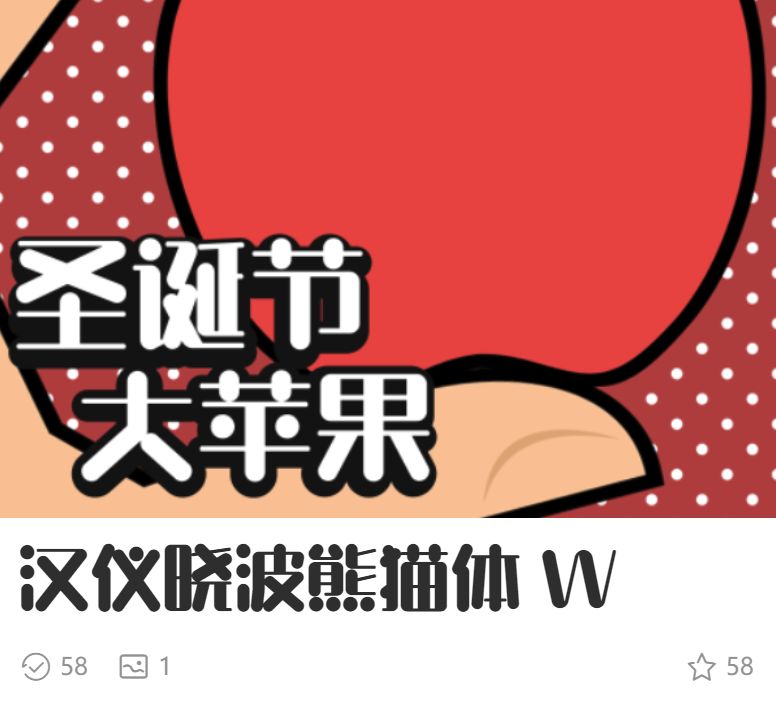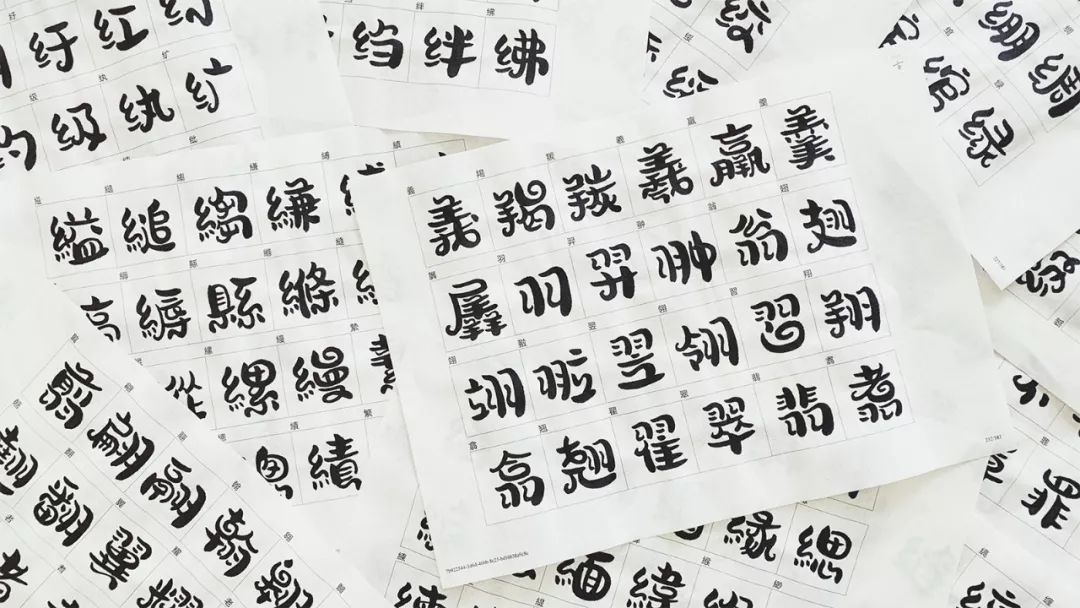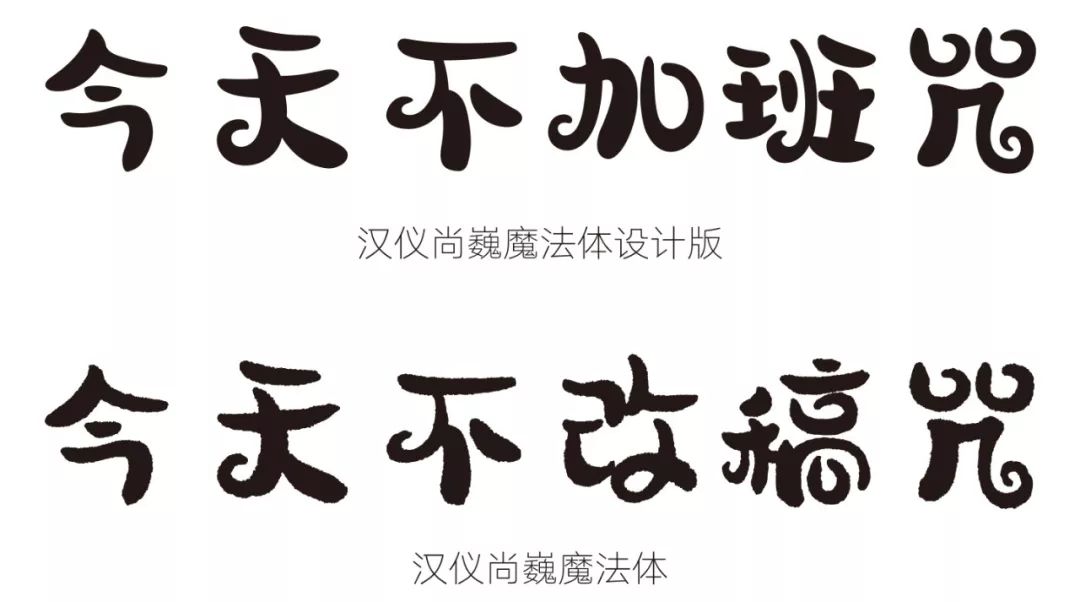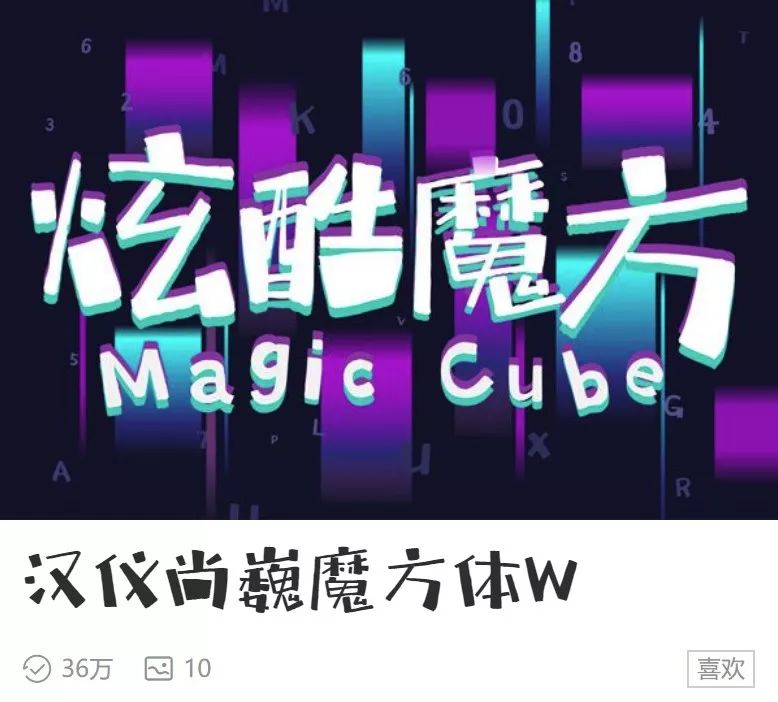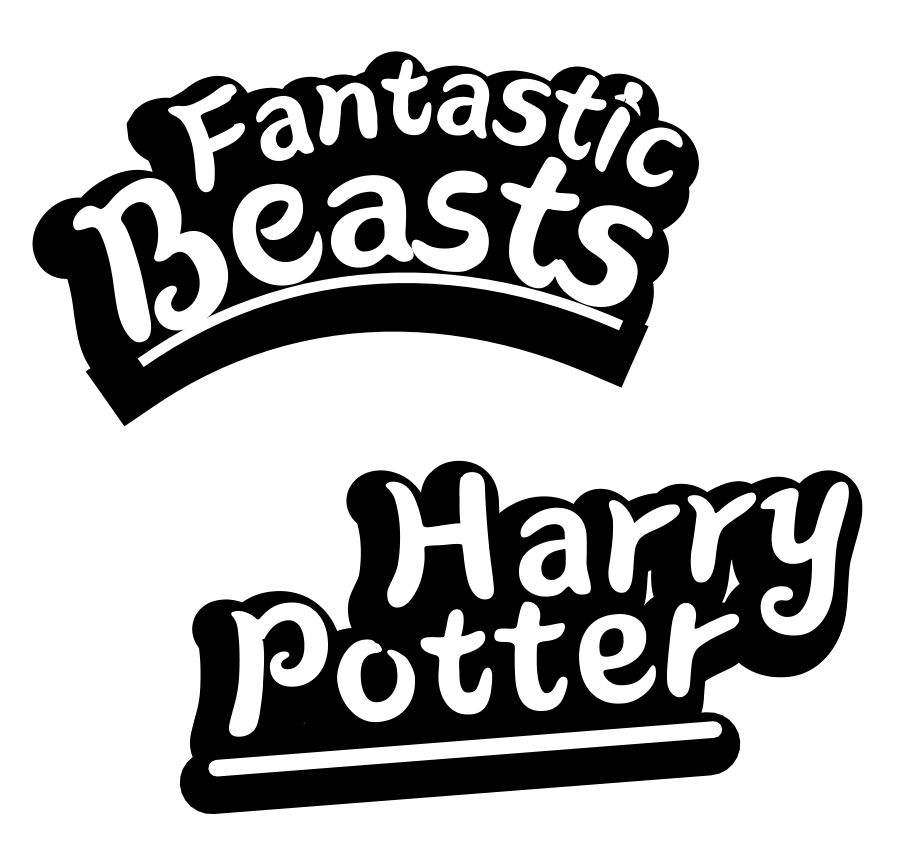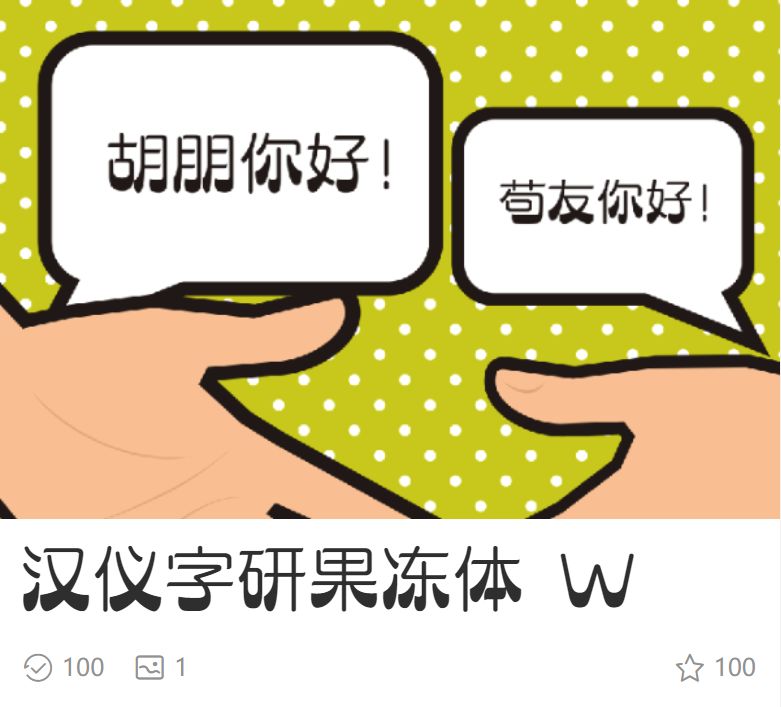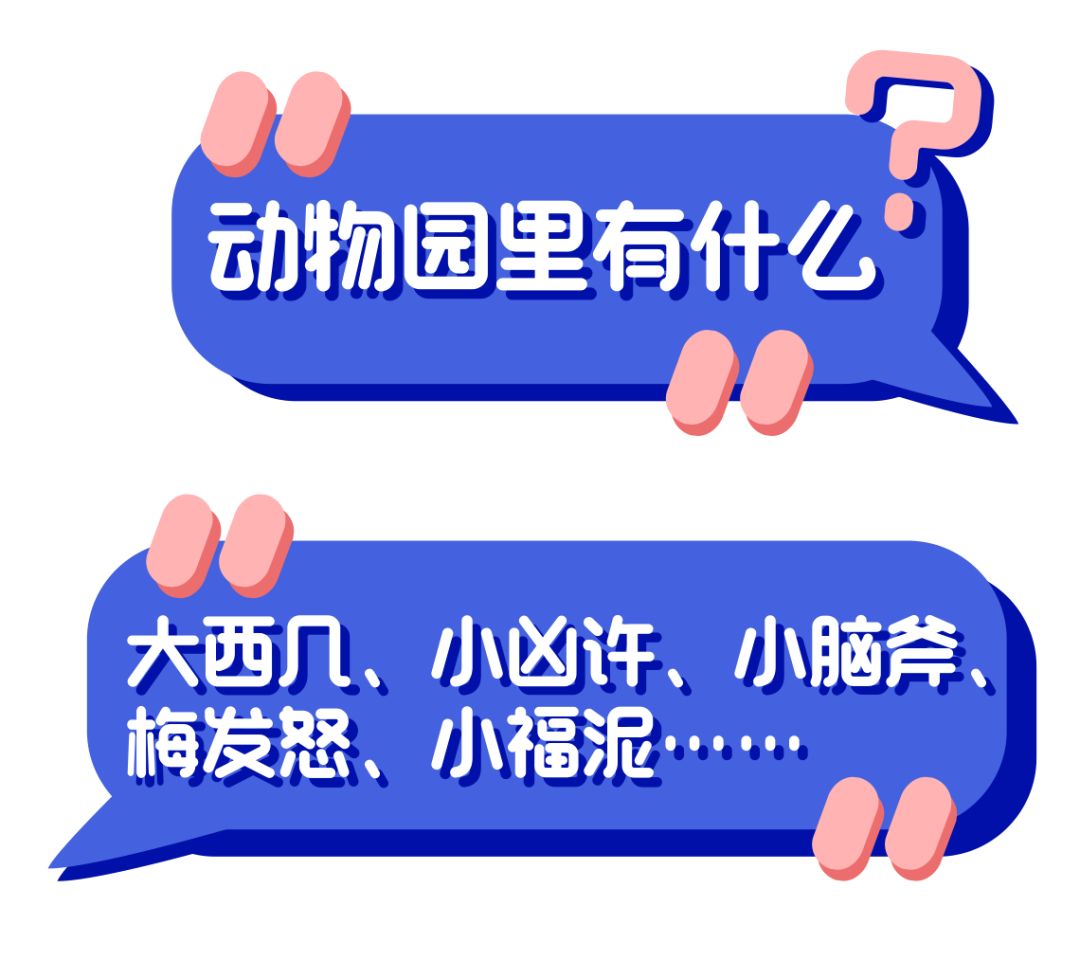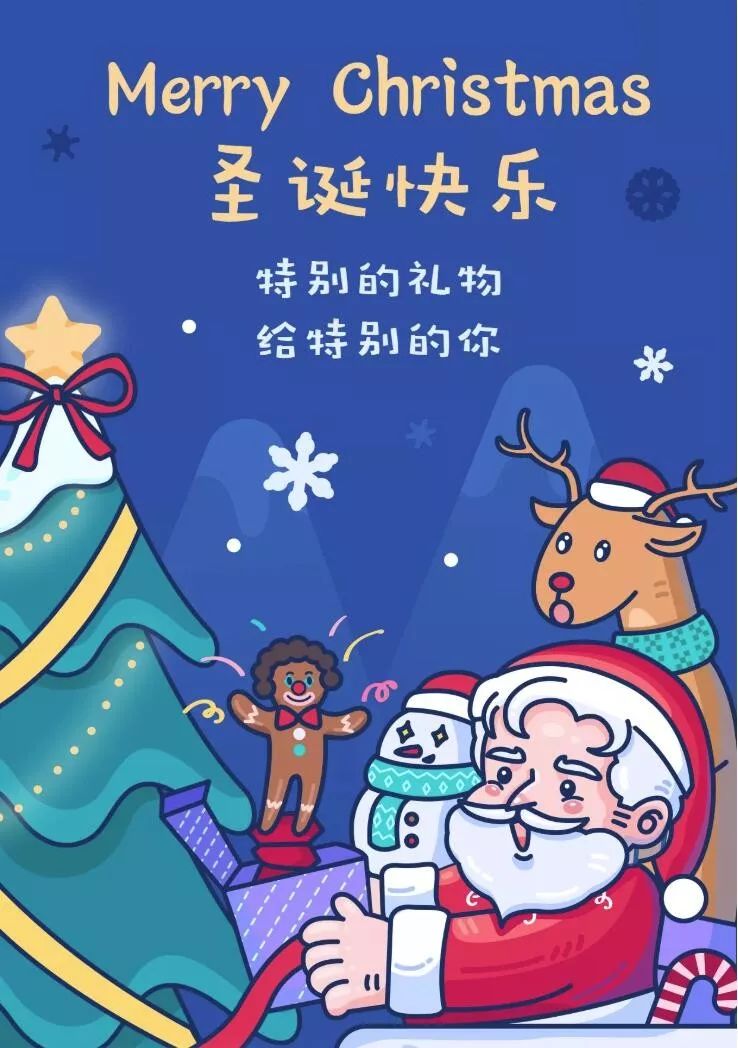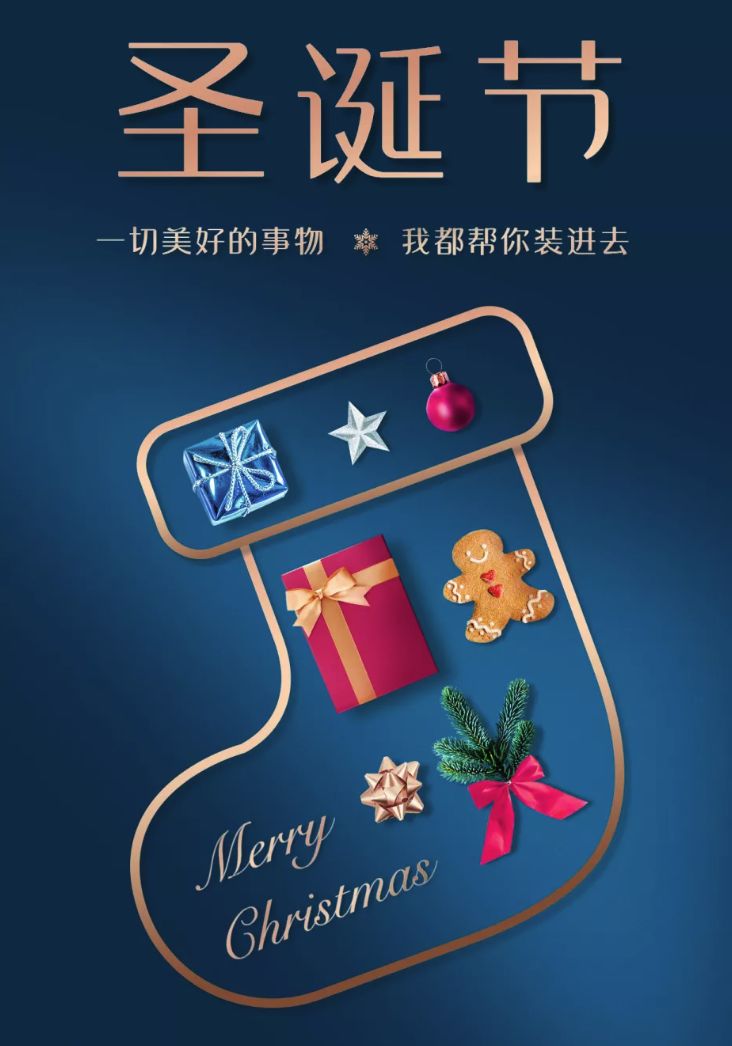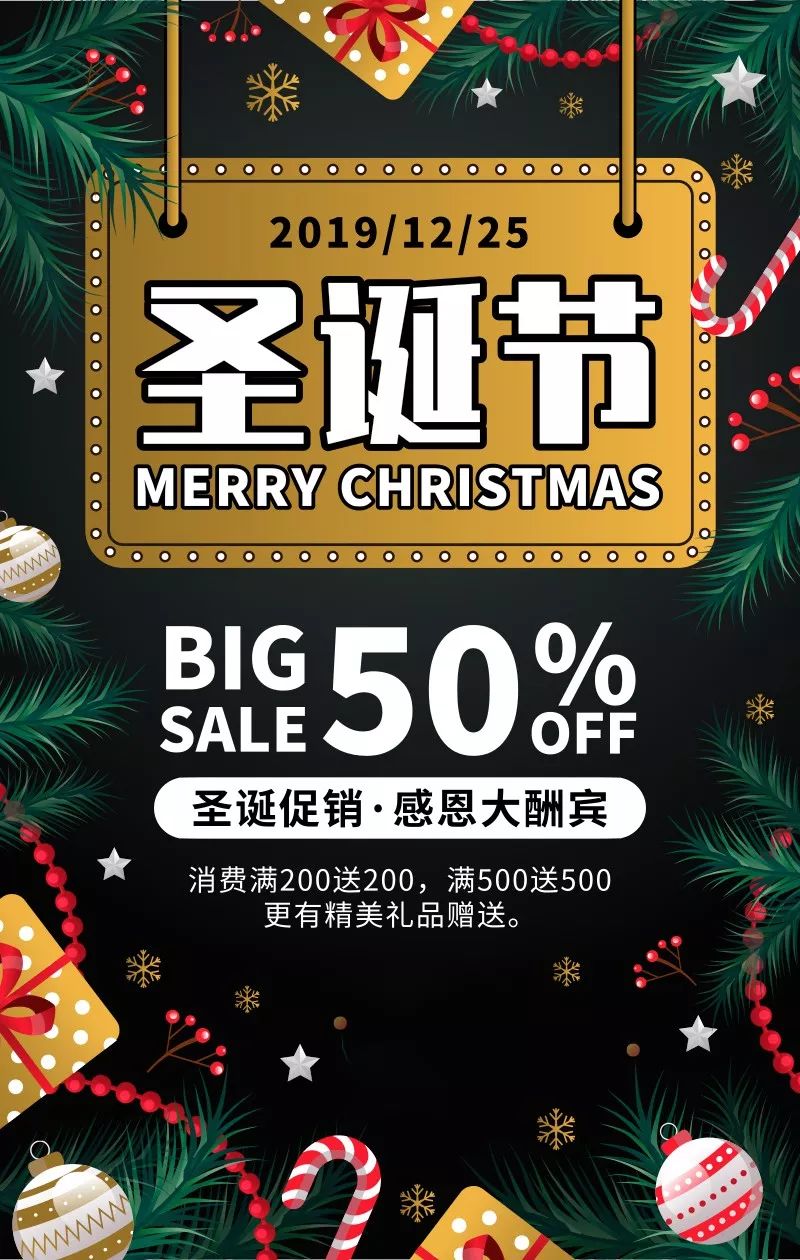
汉仪尚巍魔法体
首先登场的是尚巍的新字~
乍一看跟魔方体就差一个字,以为是兄弟款?
但其实风格千差万别,你品,你细品……
汉仪晓波熊猫体
灵感来源于熊猫那种圆滚滚的感觉,有点敦厚感,但又不失俏皮可爱。
汉仪铸字稚圆
字体笔画圆润,整体重心偏上,结构放松自然,起笔和收笔处采取开口处理,多了一分俏皮,给人温暖的视觉感受。
汉仪字研果冻体
这款字体造型独特,曲线饱满,上细下粗,有趣的同时,又稳如泰山!像它的名字一样Q弹~识别度满分!
除了上面的新字,还有一些适合圣诞主题的~
▲汉仪天真体
▲汉仪晓波敦黑
▲锐字真言体(免费商用)
▲汉仪晓波美妍体
▲汉仪瑞意宋
▲汉仪跳跳体
▲汉仪铸字木头人
▲汉仪六字黑
▲站酷庆科黄油体(免费商用)